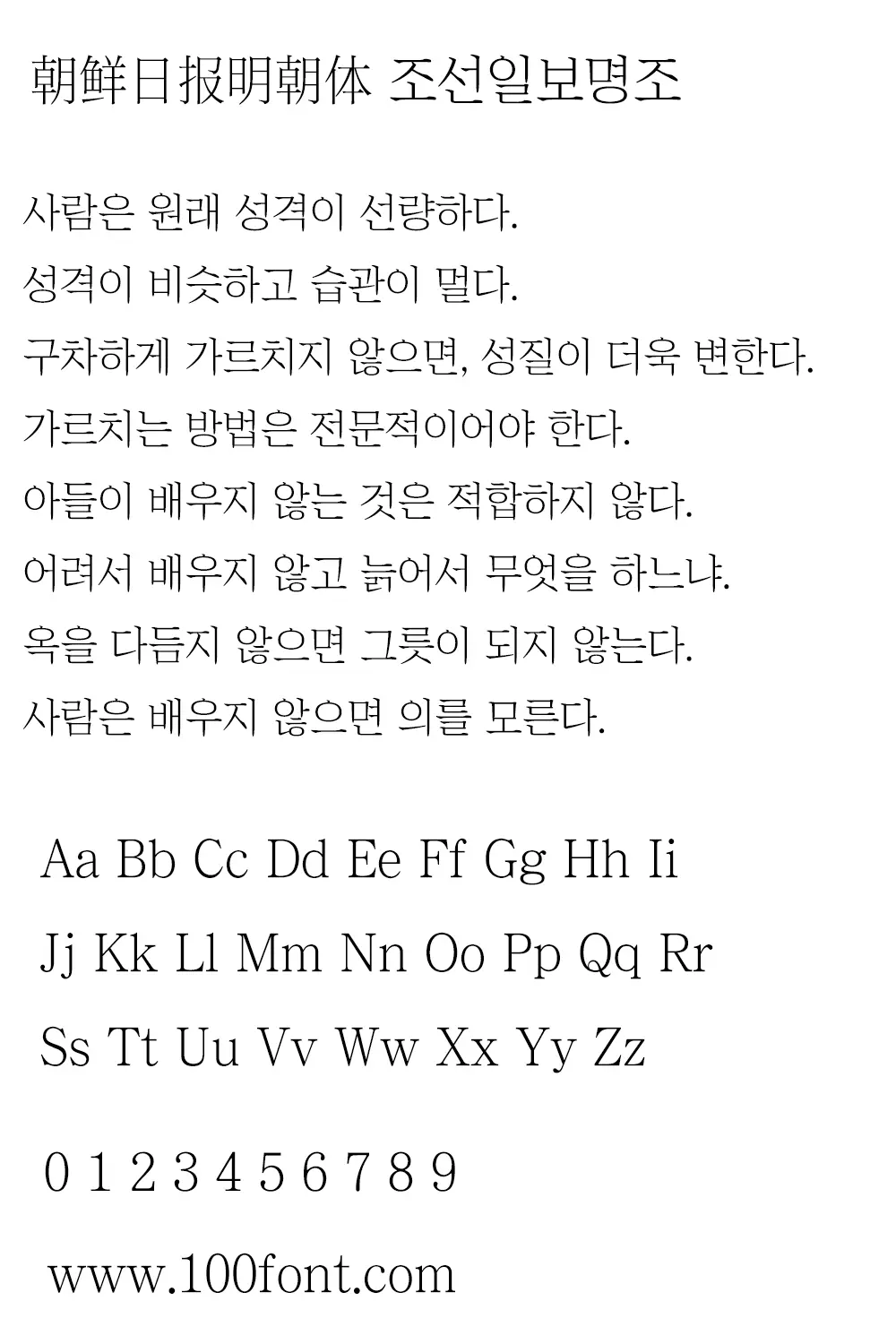
朝鮮媒體集團公開和普及報紙版面上使用的專用字體“朝鮮日報明朝體”,供任何人使用。《朝鮮日報明朝體》是1999年朝鮮日報字體開發研究所與“山石交流”製作的字體,之後總公司以一字一字的精神進行完善,提高了完成度。小尺寸使用也方便閱讀,造型美觀,深受讀者喜愛,是受到專家好評的優秀鉛字。準備好供普通PC和Mac用戶使用。
조선미디어그룹은 신문 지면에 사용하는 전용 서체(書體)인 ‘조선일보 명조체’를 누구나 사용할 수 있도록 공개·보급합니다.
‘조선일보 명조체’는 1999년 조선일보 서체개발연구소가 ‘산돌커뮤니케이션’과 만든 서체로, 이후 본사가 한 글자 한 글자 인(匠人)정신으로 보완해 완성도를 높였습니다. 작은 크기로 사용해도 읽기 편하고, 조형미가 뛰어나 독자의 사랑과 함께 전문가들로부터 호평 받아온 우수한 활자입니다. 일반PC와 Mac 사용자 모두가 쓸 수 있도록 준비했습니다.